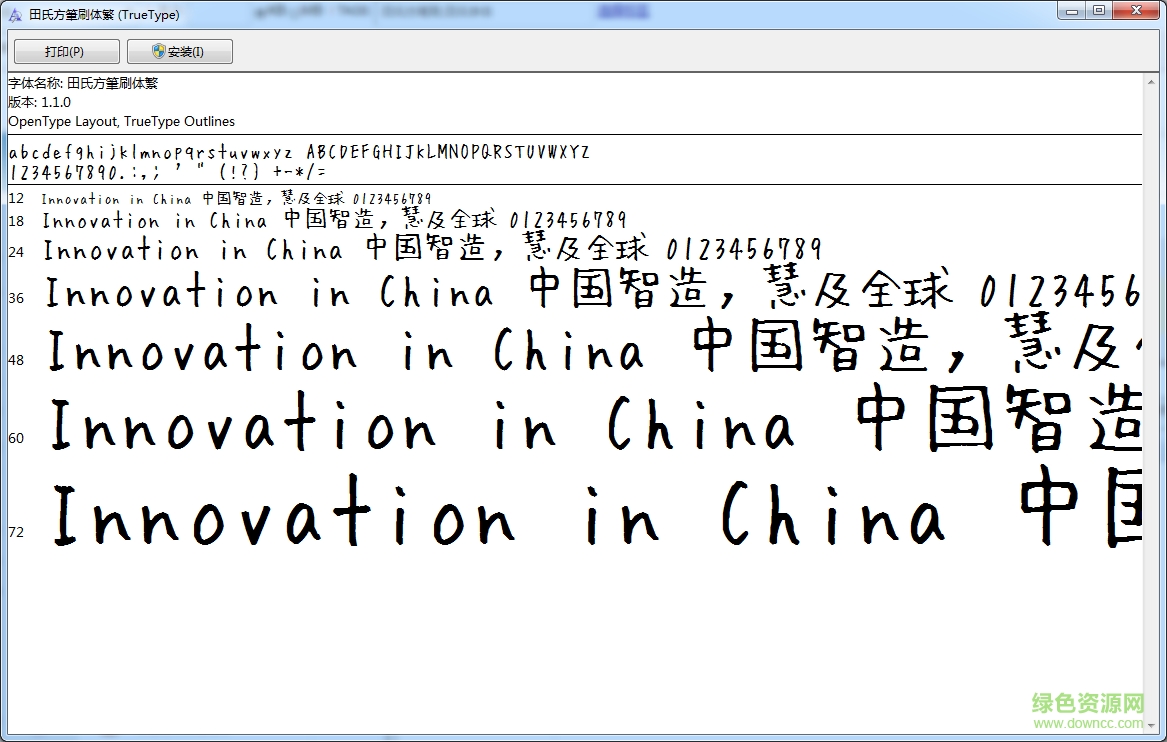
軟件介紹 軟件標簽: 田氏方筆刷 田氏字體 字體 田氏方筆刷繁體是一款非常好看的繁體字體,支持中文、英文和阿拉伯數字的輸入,字體非常的纖細,可用于用作廣告印刷和包裝等行業(yè),歡迎大家到綠色資源網下載使用!田氏方筆刷體繁安裝方法方法一:控制面板/字體/文件/安裝新字體;方法二:直接將字體復制到C:\WINDOWS\Fonts。方法三:針對win7系統(tǒng),用戶只需選中字體右鍵安裝即可。注意事項本站所有字體資源僅供個人學習與參考,如需商業(yè)使用請到相關官網授權。 軟件截圖 上一張下一張(1 / 1) 安裝詳細截圖 猜你喜歡 繁體字體 繁體字體 繁體字體有哪些?小編今天為大家推薦幾款好看的繁體字體,包含了繁體鋼筆字體、繁體隸書字體、繁體毛筆字體、繁體行楷字體等不同類型的繁體字體!廣告、PPT、海報、雜志等領域都可使用! 查看更多>> wow魔獸世界臺服字體包 2.40M/中文/0.0/ttf免費版下載 繁體書法字體 3.41M/中文/6.6/下載 楷書繁體字體包 9.76M/中文/8.0/下載 隸書繁體字體 5.46M/中文/4.2/.ttf下載 茶碗古刻繁體 5.37M/中文/5.0/下載 hyx4gf regular 3.41M/中文/8.0/下載 其他版本下載 標題 大小 更新日期 下載 下載地址 電腦版 田氏方筆刷繁體字體 點擊報錯 軟件無法下載或下載后無法使用,請點擊報錯,謝謝! 關閉報錯反饋 請描述您所遇到的錯誤,我們將盡快予以修正,謝謝! *必填項,請輸入內容 本類最新 dreamweaver字體庫 首爾南山體字體 v1.06 官方版 潮字社風云簡ttf 潮字社凌渡鯤鵬簡體字體 潮字社曾玉波手書簡字體 微博慧心字體 相關文章 Photoshop字體安裝使用方法和技巧 如何解決“無法新增字體”問題 Win 7系統(tǒng)安裝字體方法 網頁字體大小設置方法 怎么改網頁字體大小 在Linux系統(tǒng)中安裝字體的幾種方法 windows7字體顯示問題:打開某些程序的時候顯示的是亂碼 用戶評論 熱門評論 最新評論 發(fā)表評論 查看所有評論(0) 昵稱: 請不要評論無意義或臟話,我們所有評論會有人工審核. 字數: 0/500 (您的評論需要經過審核才能顯示)